无论是线上开设店铺还是线下派发传单,大家都能见到美工字体,它好看与否,直接关系着整个页面的美观程度,美工字可以线上获取,也可以线下自己书写,那么,美工字体下载怎么选择好看呢?
一般来说,如果是体现男性为主导的文章或是页面的时候,就需要让整体的文字看起来显得比较硬朗,比较符合男子气概,体现一种力量之美,稳重之美,彰显出男子大气概。因此,一般要选用笔画比较粗的美工字,让字体看起来有棱有角,粗细搭配,显得更加有条理。
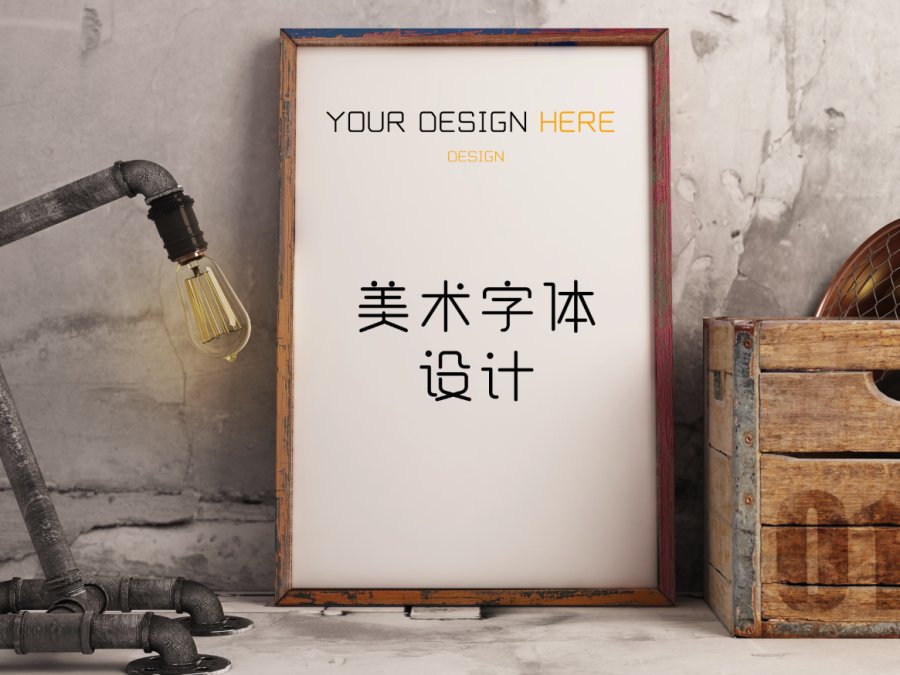
如果是体现女性为主导的文章或是页面的时候,就要充分体现女性柔美的一面,可以是活泼的样子,可以是秀丽的样子也可以是成熟时尚的气息。因此,美工字要选用一些比较纤细,流畅的线条,字形要多突出变化。
当页面是为了想要尽量销售产品,进行促销的时候,选择的美工字一定是要比较显眼的,或者经常使用变形的字体来抓住顾客的眼球,这样才能一瞬间让顾客看到文章的中心,一眼让他们知道商品的好处。奢华型的页面一般使用的美工字要简约优美,干净利落,最好配上英文的字体,显得高贵时尚。
以上就是关于美工字如何书写的三种情况,大家可以根据不同的场景选用不同的美工字。